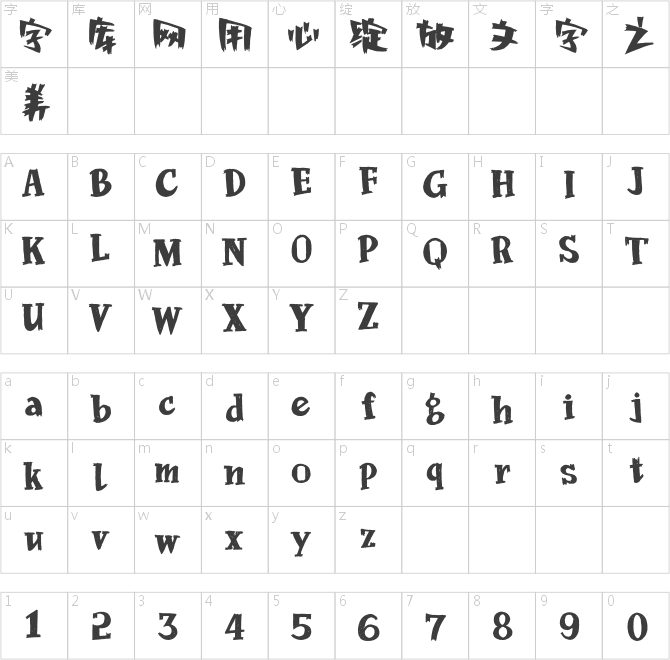
方正法小珂體簡 詳情頁
字體名稱: 方正法小珂體簡
方正法小珂體簡
方正法小珂體,從字形來看并不規矩,如同長歪了的樹,每個字都打破傳統字形規范,重心右傾,左右上下各部分大小比例鮮明,卻生出自有的平衡體系和風格,兼具笨拙 、直率、質樸、隨性、懶散、童真,枯筆效果可能還帶出一點颯。“任性的灑脫,克制的浪漫”,大概就是這樣子吧。適用于獨立,喜與眾不同,文藝情懷愛好者,應用于標題,包裝,海報,廣告,文化印刷品及周邊。